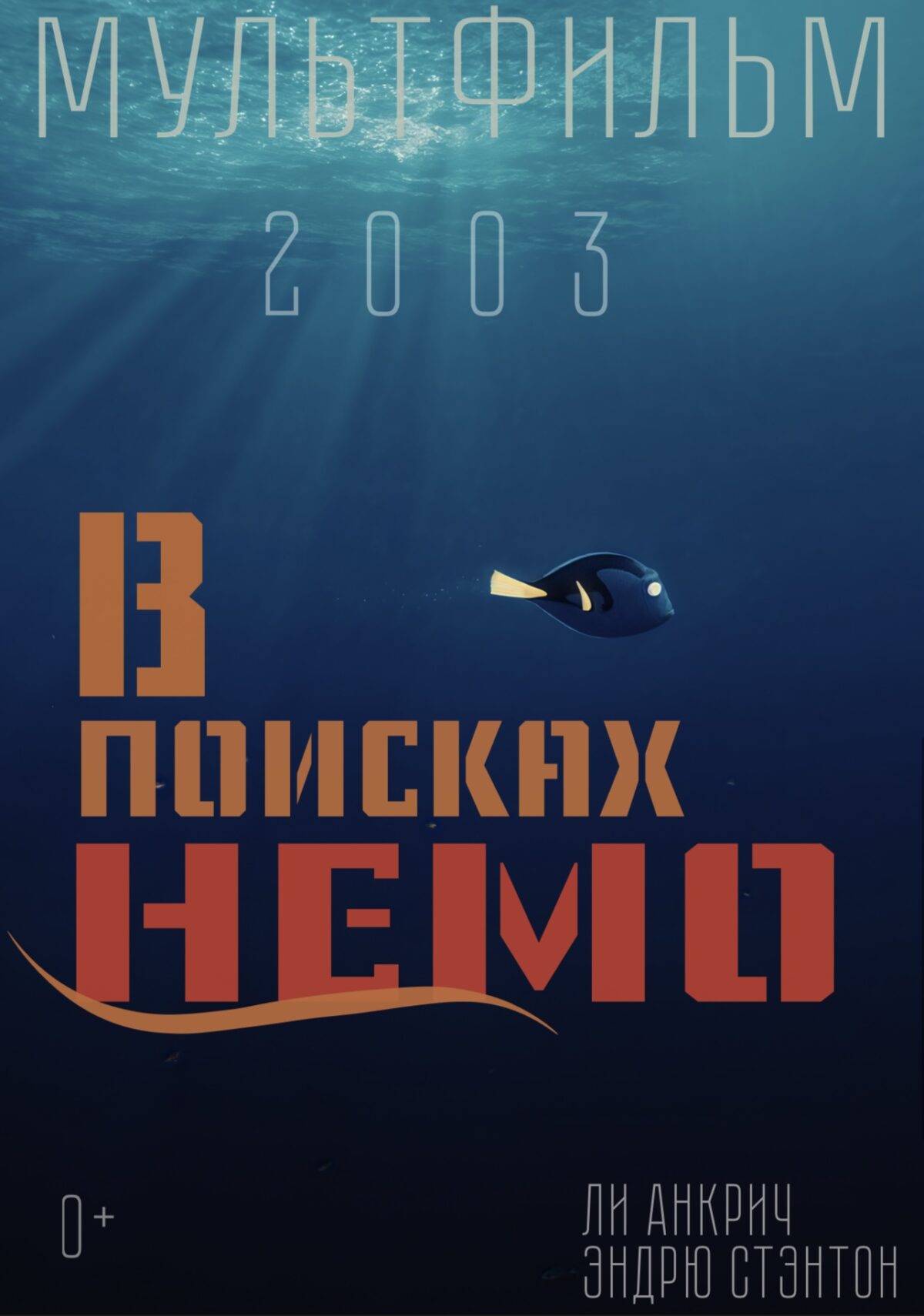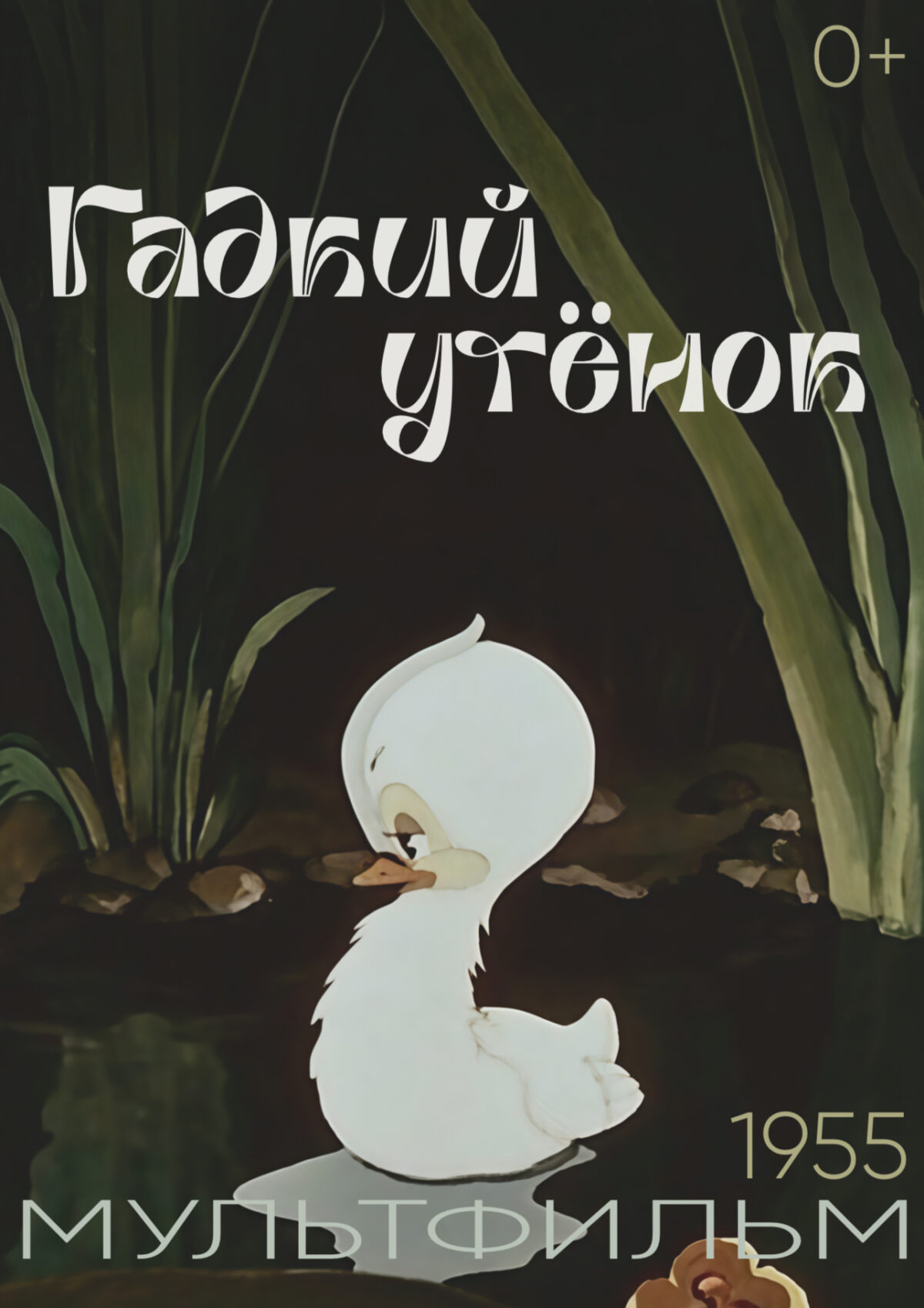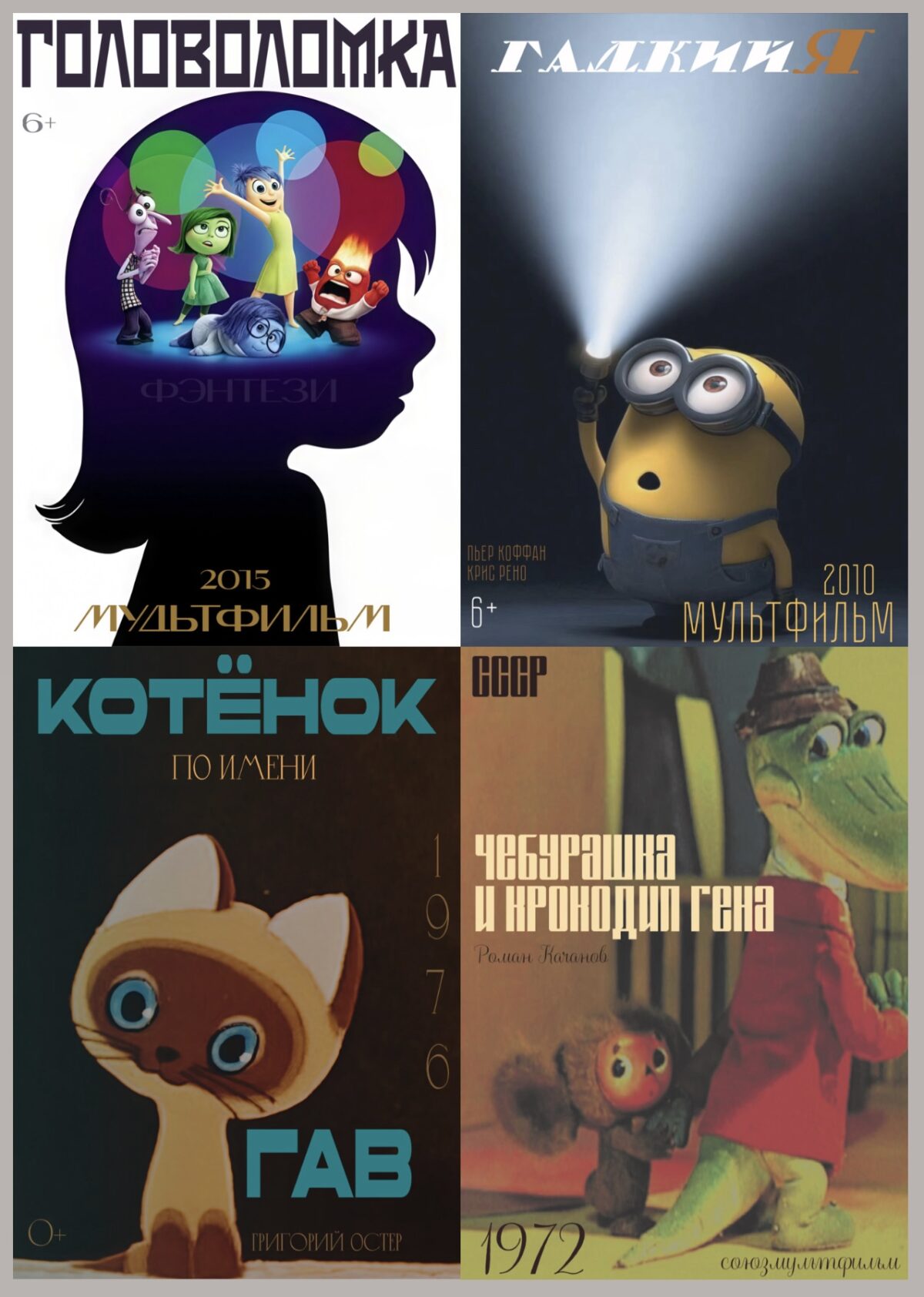
Афиша — это первый контакт зрителя с фильмом. Обычно дизайнер подбирает шрифт, созвучный визуальному стилю анимации: ретро-шрифт к рисованной классике, футуристический — к 3D-блокбастеру. Но иногда рождается идея сделать наоборот. И это не ошибка, а осознанный приём с мощным эффектом.
Что происходит?
Советские шрифты — это не просто гарнитуры. Они несут отпечаток эпохи: конструктивистский пафос 1920-х, индустриальную суровость 1930-50-х, плакатную броскость 1960-70-х, позднесоветский минимализм. Наложение этого кода на современную компьютерную анимацию создаёт зазор.
Какие смыслы рождаются?
· Ирония и деконструкция. Брутальный советский рубленый шрифт на афише доброго семейного 3D-мультфильма звучит как издевательский комментарий: «А давайте-ка превратим этих милых зверушек в пропагандистский плакат?» Работает для фестивальных версий, сатирических трейлеров, альтернативных постеров.
· Ностальгия по будущему. Если современный мультфильм сам отсылает к советской эстетике (например, стилизованная графика или ретро-фантастика), то советский шрифт не ломает, а достраивает образ. Это приём «ложной памяти»: зритель думает, что уже видел такой плакат в детстве, хотя мультфильм новый.
· Идеологический подтекст. Крупный жирный шрифт с резкими углами, напоминающий лозунги, превращает постер в политическое высказывание. Даже без слов зритель считывает: «Этот мультфильм — про серьёзное, возможно, про борьбу».
Что происходит?
Классические рисованные мультфильмы, созданные от руки на целлулоиде, получают типографику XXI века. Геометрические гротески, переменные начертания, кислотные нео-антиквы, леттеринг-стили соцсетей.
Какие смыслы рождаются?
· Омоложение и актуализация. Советский мультфильм перестаёт быть «старым». Он входит в мемную культуру, становится пригодным для тикток-промо, модных мерч-коллабораций, ремиксов. Зритель-подросток воспринимает его не как наследие прошлого, а как актуальный контент.
· Контраст текстур. Грубый акварельный фон или карандашный контур персонажа в сочетании с гладким, «пластиковым» современным шрифтом создаёт напряжение между рукотворностью и цифрой. Это часто используют на постерах фестивалей анимации, когда хотят показать уникальность старых техник на фоне новых медиа.
· Абсурд и сюрреализм. Если взять минималистичный гротеск (Helvetica, Inter) и наложить на абсурдный советский сюжет, возникает эффект «официального документа о странном». Это игра с серьёзной формой и несерьёзным содержанием.
Чтобы такая афиша работала, а не выглядела как ошибка верстальщика, соблюдайте три условия:
1. Осознанность. Зритель должен чувствовать, что разрыв эпох — это задумка, а не случайность. Для этого добавьте хотя бы один элемент, который «скрепляет» чуждые миры: общий ритм, повторяющийся цвет, единую композицию.
2. Дозирование. Не превращайте афишу в винегрет. Если взяли советский шрифт — остальные элементы (иллюстрация, рамки, графика) могут быть нейтральными или тоже слегка стилизованными. Перегруженность убивает эффект.
3. Аудитория. Для фестиваля экспериментальной анимации такие приёмы — норма. Для широкого проката семейного мультфильма — риск провала. Всегда проверяйте, поймёт ли зритель ваш посыл.
Использовать шрифты не по эпохе — это не модный тренд, а инструмент переозначивания. Он позволяет превратить афишу из простого анонса в высказывание. Главное — не смешивать ради смешивания, а задавать себе вопрос: «Какую новую мысль я хочу вложить в этот старый сюжет или какой старый шрифт может оживить эту новую картинку?»
Если ответ есть — смело ломайте ожидания зрителя.